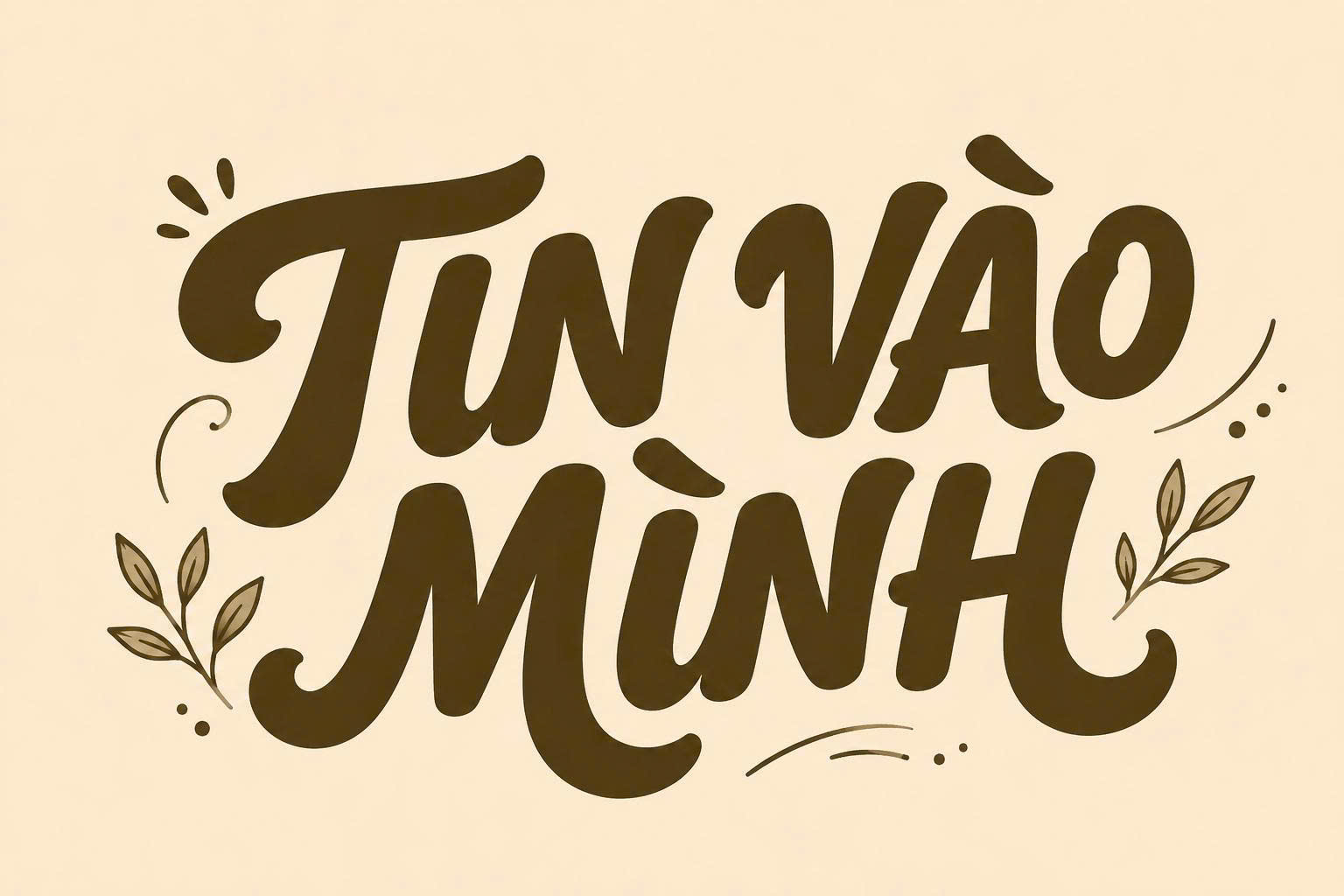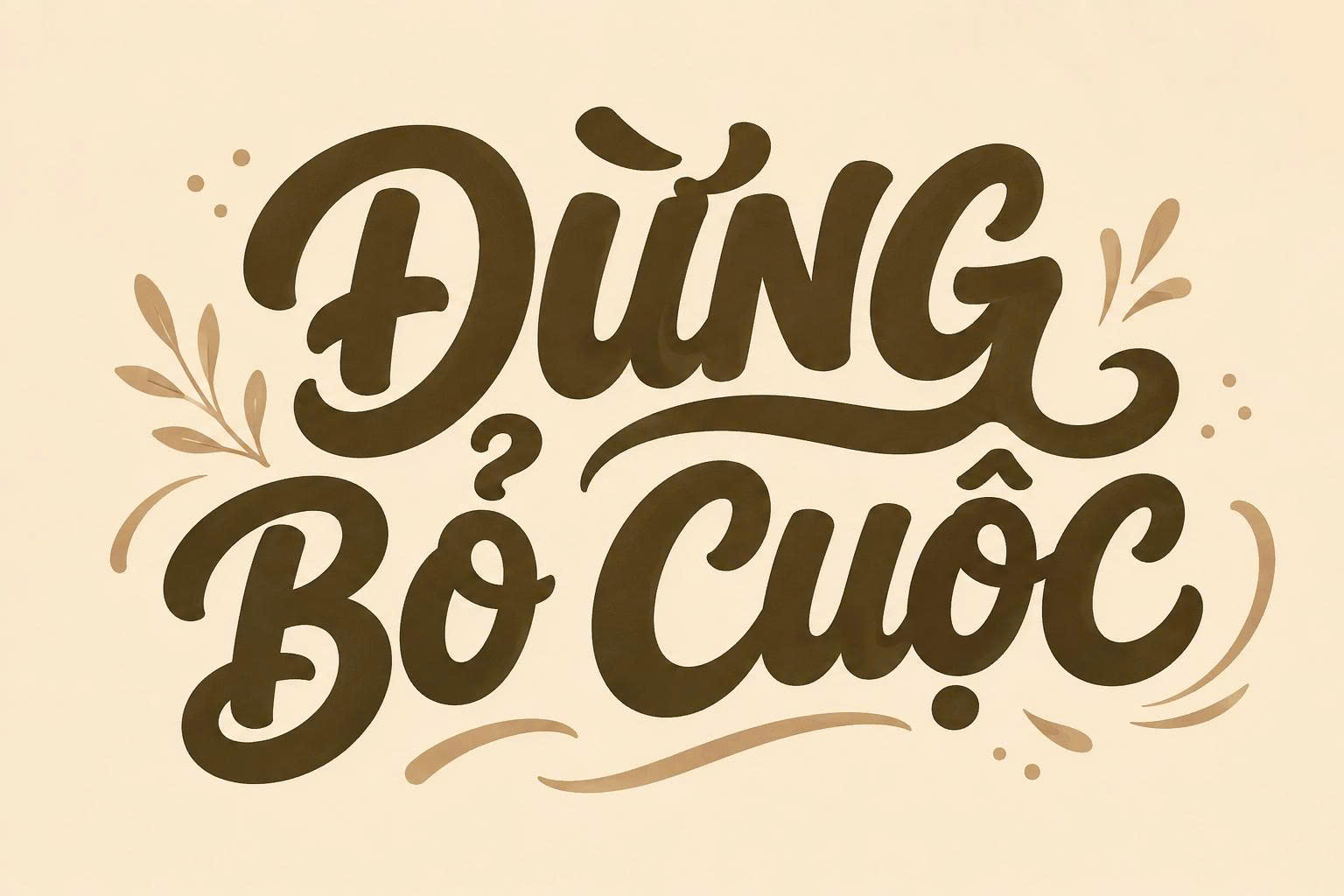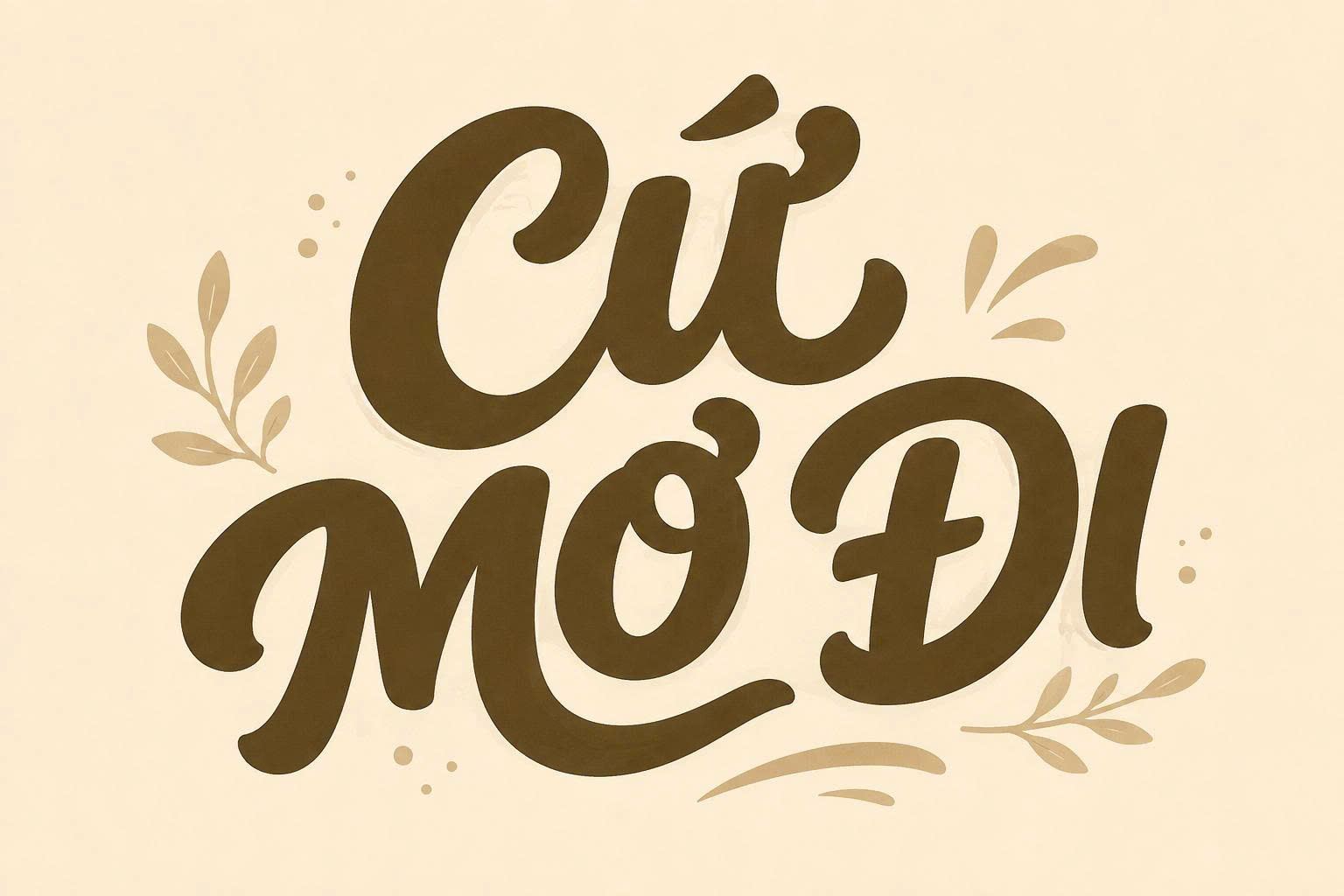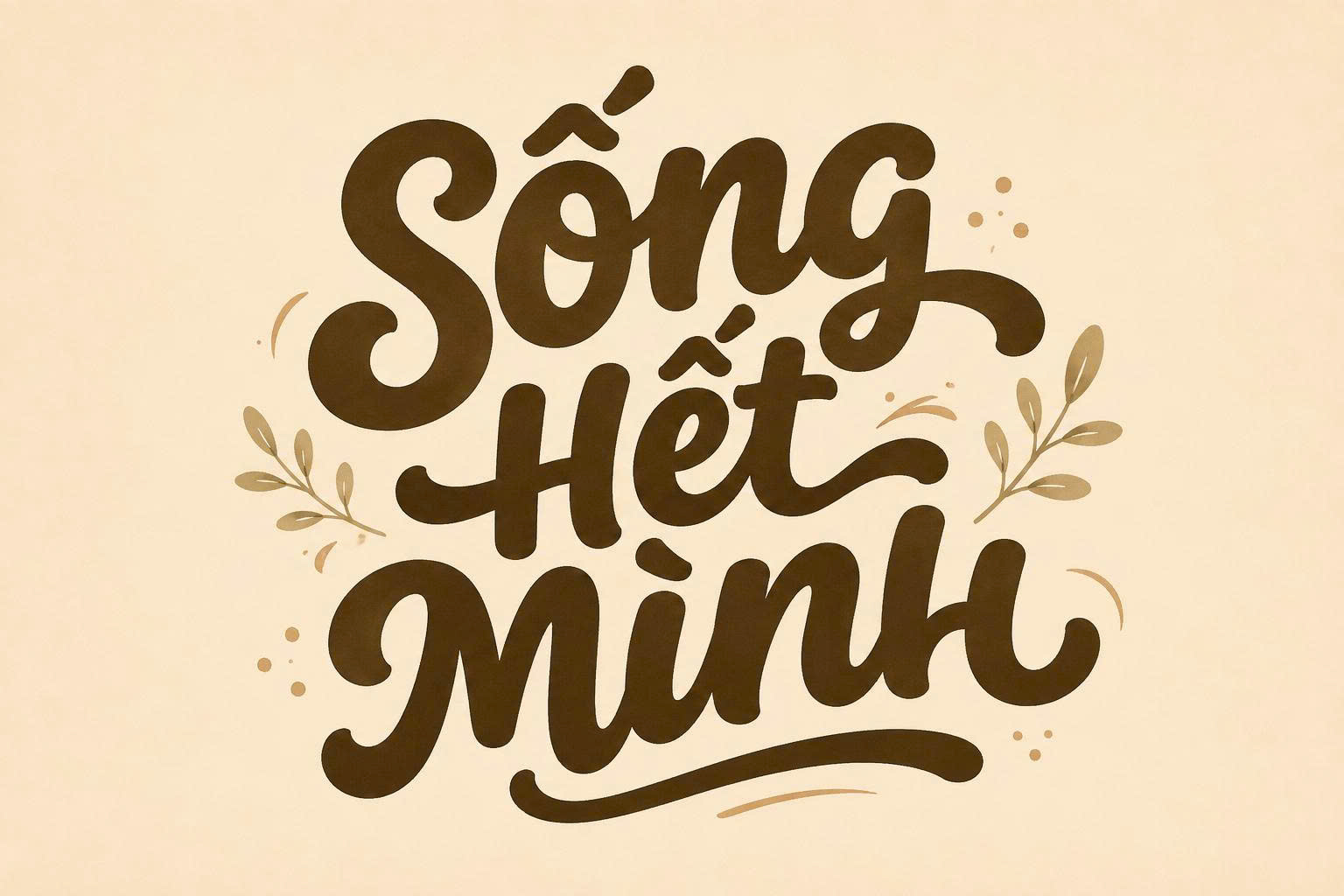
Font Việt hóa SVN Salty Script là bộ font chữ dạng brush script mang phong cách viết tay đầy phóng khoáng, tự nhiên và tràn đầy năng lượng. Với những đường nét mô phỏng nét cọ vẽ có độ xước nhẹ, đây là công cụ hoàn hảo cho các thiết kế logo, bao bì sản phẩm hoặc các ấn phẩm quảng cáo cần sự phá cách và trẻ trung. Doozypack.vn cung cấp bộ file tải SVN Salty Script Việt hóa chuẩn, giúp bạn xử lý nội dung tiếng Việt mượt mà mà vẫn giữ nguyên được tinh thần nghệ thuật của bộ font gốc.
Đặc điểm thẩm mỹ của font Việt hóa SVN Salty Script
Salty Script không đi theo quy tắc chỉn chu của các dòng font thư pháp truyền thống mà tập trung vào sự ngẫu hứng và mạnh mẽ của nét cọ brush.
Nét vẽ tay tự nhiên với cấu trúc brush xước
Điểm độc đáo nhất của SVN Salty Script chính là cấu trúc “xước” tự nhiên trong từng nét chữ. Những khoảng hở nhỏ li ti trong nét cọ tạo cảm giác như chữ được vẽ trực tiếp bằng sơn hoặc mực khô trên bề mặt thô ráp. Điều này giúp thiết kế của bạn có chiều sâu hơn, mang lại hiệu ứng thị giác mạnh mẽ và đậm chất thủ công.
Phong cách năng động cho các dự án mùa hè và thực phẩm
Đúng như tên gọi “Salty”, bộ font này mang hơi hướng của biển cả, sự tự do và năng động. Nó cực kỳ phù hợp cho các thiết kế liên quan đến chủ đề du lịch, thể thao, đồ uống giải khát hoặc các loại thực phẩm fast-food. Các ký tự được sắp xếp với độ cao thấp không đồng đều, tạo ra một nhịp điệu vui tươi cho dòng văn bản.
Trong giới thiết kế đồ họa tại Việt Nam, cụm từ font Việt hóa SVN đã trở thành một bảo chứng cho chất lượng. Các font chữ thuộc nhóm SVN được đội ngũ Style Việt hóa thực hiện rất kỹ lưỡng, tập trung vào việc xử lý các dấu thanh tiếng Việt sao cho không bị đè nét hoặc quá xa ký tự gốc. Việc sử dụng các font trong hệ sinh thái SVN giúp bạn tiết kiệm thời gian chỉnh sửa khoảng cách chữ (kerning) và đảm bảo tính thẩm mỹ đồng nhất cho toàn bộ ấn phẩm.
03 Ứng dụng thực tế của SVN Salty Script trong in ấn bao bì
Nhờ vẻ ngoài cá tính, SVN Salty Script thường xuyên xuất hiện trên các sản phẩm in ấn thực tế do Doozypack.vn sản xuất:
- In túi giấy thời trang: Đặc biệt là các dòng túi cho shop đồ thể thao hoặc thời trang dạo phố, font chữ này tạo nên sự phá cách ngay từ cái nhìn đầu tiên.
- Hộp giấy đựng thực phẩm: Các quán cà phê, tiệm bánh hoặc cửa hàng đồ ăn nhanh thường dùng Salty Script làm tiêu đề trên hộp giấy để tạo cảm giác ngon miệng và thân thiện.
- Tem nhãn sản phẩm: Phù hợp cho các dòng sản phẩm “Organic” hoặc “Handmade” cần nhấn mạnh tính tự nhiên và quy trình sản xuất thủ công.
04 Lưu ý kỹ thuật từ xưởng in Doozypack khi sử dụng font SVN Salty Script
Sử dụng các font chữ có nhiều chi tiết xước như SVN Salty Script trong sản xuất bao bì cần lưu ý các vấn đề kỹ thuật sau để tránh thành phẩm bị lỗi:
- Hạn chế in lụa (Silk Screen) chi tiết nhỏ: Các lỗ xước li ti của font Salty Script rất khó hiển thị rõ ràng khi in lụa trên bề mặt vải hoặc giấy nhám. Nếu in kích thước nhỏ, các nét xước này có thể bị bít mực.
- Cẩn trọng khi ép kim (Hot Stamping): Việc ép kim đòi hỏi các nét chữ phải có độ liền mạch nhất định. Khi ép font brush xước, thành phẩm có thể trông giống như bị bong tróc kim loại. Bạn nên “clean” bớt các chi tiết xước nhỏ trước khi làm khuôn ép kim.
- Kiểm tra hệ màu CMYK: Các nét xước của font thường tạo ra nhiều lớp màu chồng lấn. Hãy đảm bảo file thiết kế của bạn đã chuyển về hệ màu CMYK để tránh việc màu in ra bị tối hoặc xỉn so với màn hình RGB.